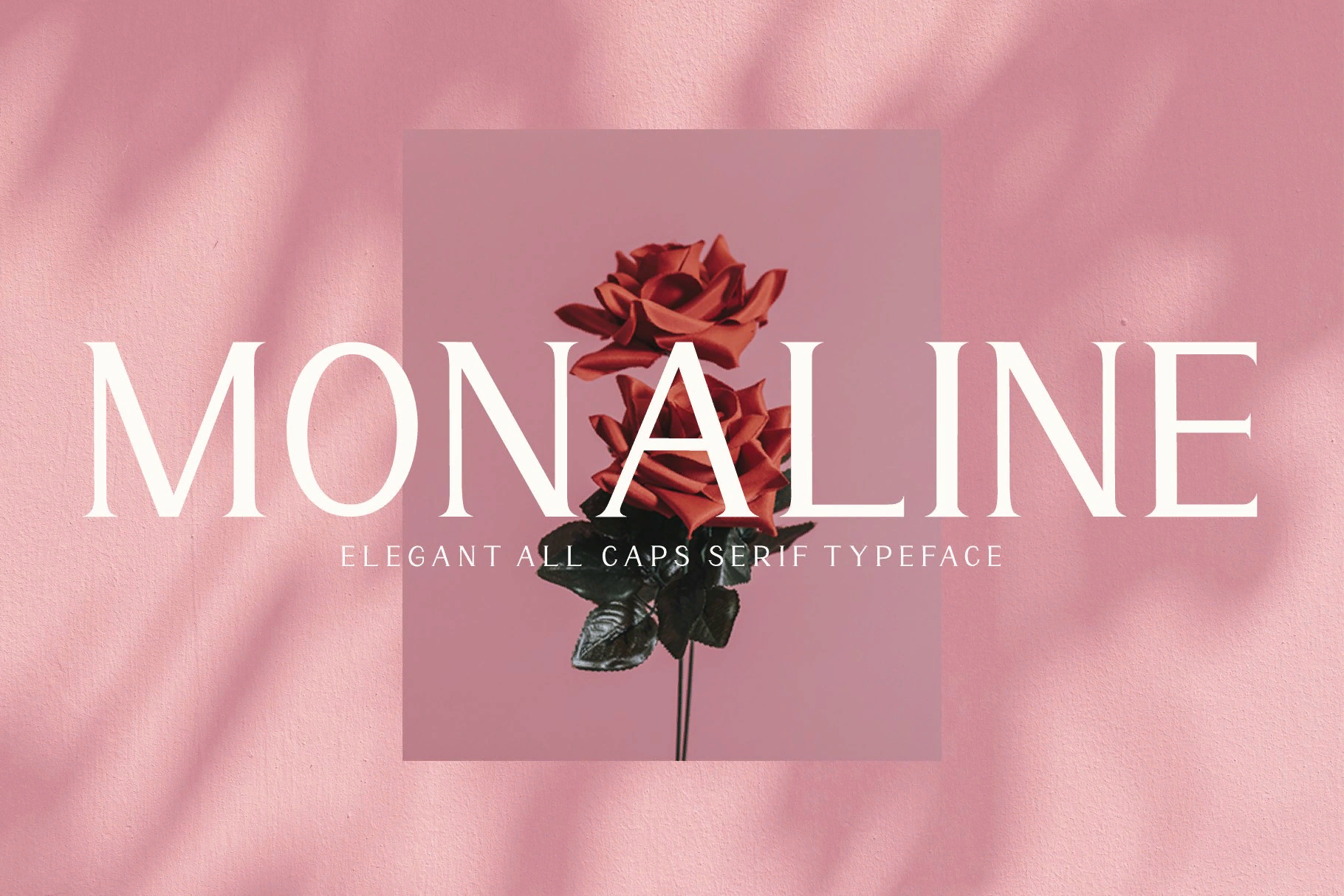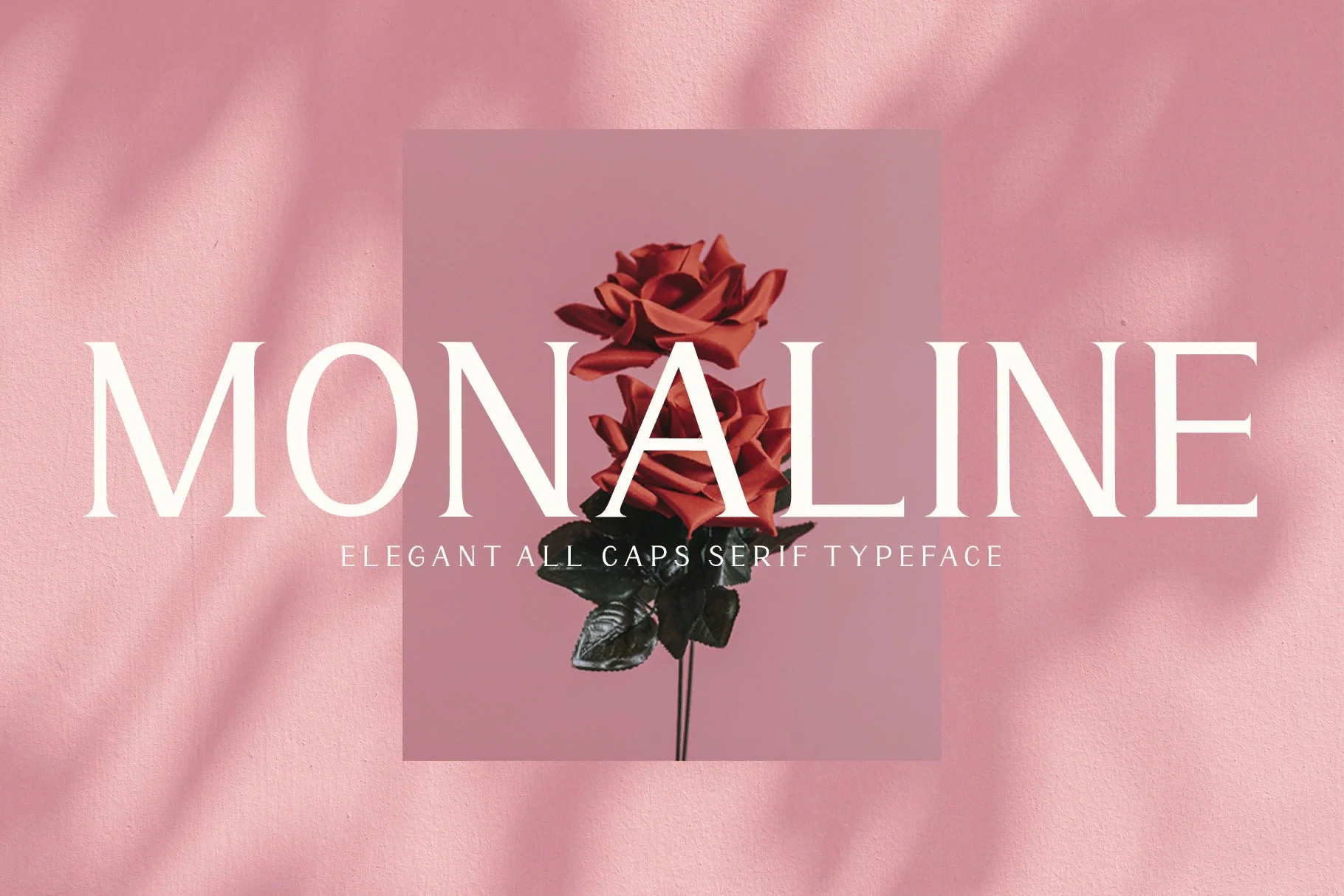
Название: Monaline Font (2021)
Monaline - это элегантный и современный шрифт с засечками.
Он идеально подходит для логотипов, бизнес-брендинга, написания веб-дизайнов, визитных карточек и практически всего, что требует уникального штриха.